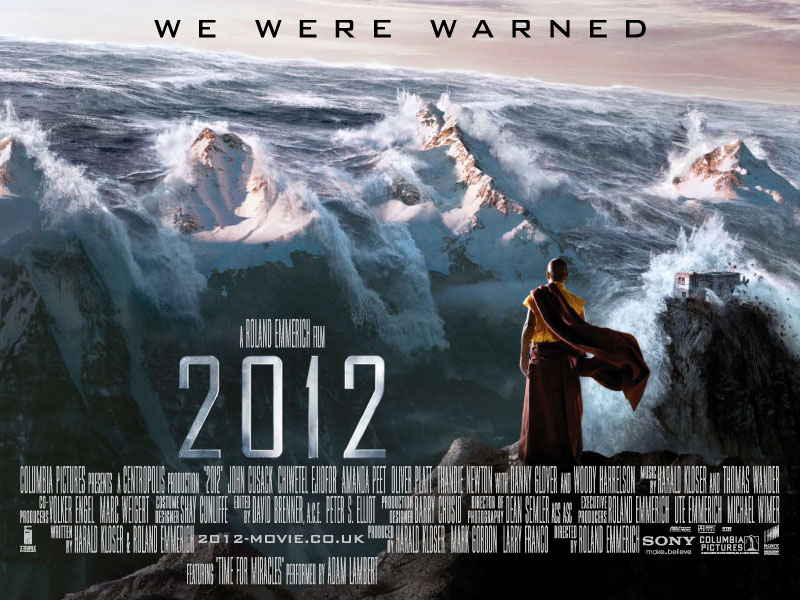
Nhân ngày 14/3-Valentine trắng. Nhận việt hóa Font theo yêu cầu miễn phí
Như tit mình sẽ việt hóa Font cho 10 người đầu tiên comment tại đây, coi như làm quen với mọi người trong diễn đàn !! :D
Yêu cầu:
• 1 người 1 font.( kèm link tải ngay trong cmt )
• Font có đầy đủ ký tự nhé.
• Font nhìn rõ ràng một tí nhé mọi người :)
Vd như font này mình sẽ làm.
[​IMG]
Còn như font này thì ngược lại ;)
[​IMG]
Gợi ý: Font càng đẹp càng tốt, bởi vậy với có hứng làm nhé các ace :))
font bác để link chung luôn nhé ;)) lười tìm có font đẹp thì down thôi :+1:
Ồ hố !! Bác ơi !! Việt hóa dùm e con lày nhé :D
Font "đập" nuôn đới !! :3
Việt hóa giùm mình font này nhé bạn :D Font name: Gosmick Sans
1 Font trong số 4 font con :D
Bạn chọn Font nào để mình làm ?
Bạn đọc kỹ yêu cầu nhé.
Bác ơi Việt Hóa hay có thể share em cái font để viết chữ poster dạng này không ạ?
Cái dòng chữ bên dưới ghi tên Đạo diễn, Diễn viên, quay phim, ánh sáng ấy ...
kiểu đầu tiên regular đó bạn, font này khá đẹp để làm truyện :D
Nếu được bác làm cho em cái này, em đội ơn bác luôn, vào trang ít chữ còn đỡ chứ vào trang nhiều chữ thì chỉ muốn phang em xuống nền luôn ^:)^
Thử tự mò mà chịu luôn, khó vãi luyện.. cái font chỗ màu xanh lá mạ bị lỗi tiếng việt đó bác.